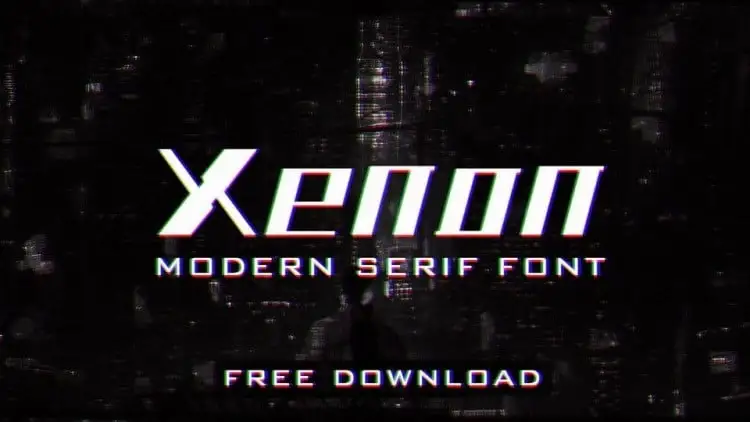
Xenon Display Font é uma paleta de fontes sans-serif bold e autêntica criada por Satheesh Chandran. Com o design minimalista e futurístico, esta fonte traz versões tanto regular quanto bold para um toque moderno que se encaixa perfeitamente em ambientes de exibição digital. A palavra Xenon (ξένος – xenos em grego) significa “foreigner” ou “guest”, refletindo a ideia de ser algo novo e inovador, mas também familiar ao mesmo tempo. Este é um lote perfeito para aqueles buscando uma fonte versátil e poderosa que se destaca em qualquer aplicação visual. Seja para rótulos, design gráfico ou qualquer uso onde desejar transmitir modernidade e distinção, a Xenon Display Font está aqui para ajudar você a destacar-se.